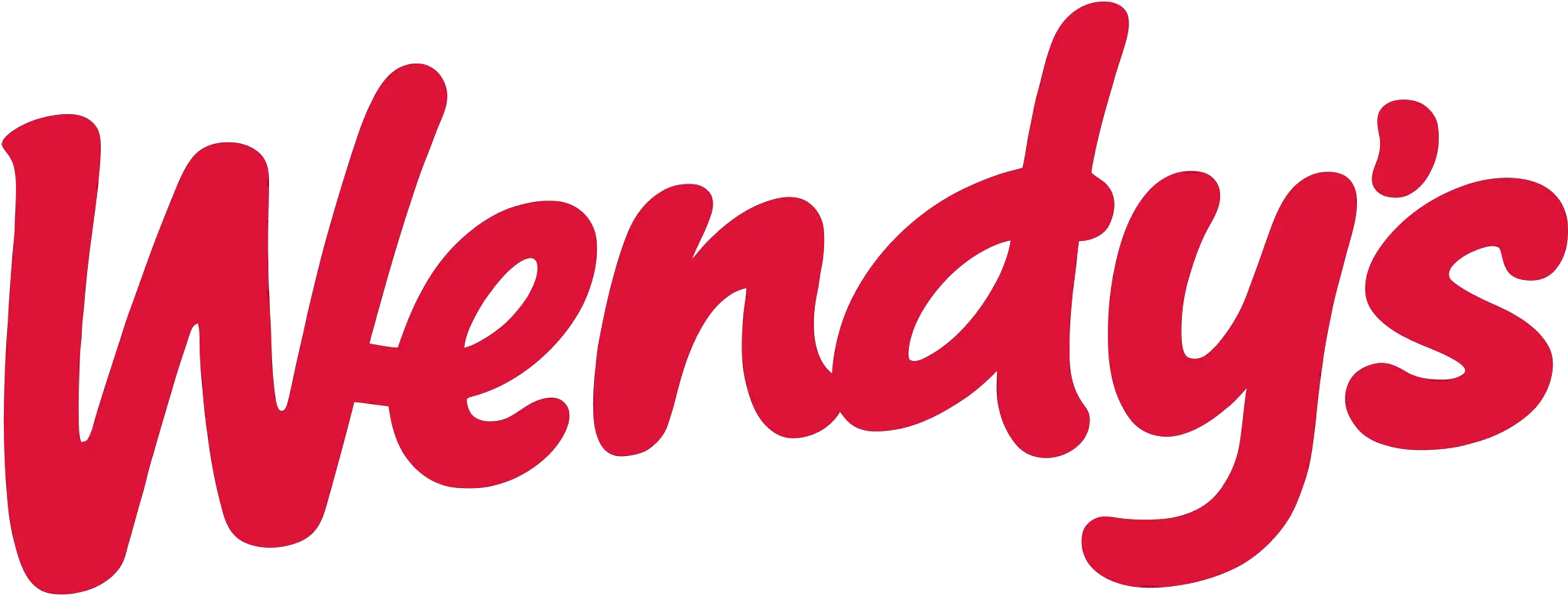
Wendys Logo Schriftart (alt & neu)
Wendys Logo verwendet welche Schriftart?
Bei der Gestaltung des Logos von Wendy wurde ein bestimmter Satz von Spezifikationen befolgt, aber es ist schwierig, eine bestimmte Schriftart zu bestimmen, die für die Erstellung des Logos verwendet wurde.
Trotzdem sind die Wendy's Script- und Wendyville- Schriftarten der Wendy's-Logotype-Schriftart auffallend ähnlich, die sich auf Wendy's Script überträgt.
Alternativen und ähnliche Schriftstile zu Wendy's Script und Wendyville
Das Folgende sind 5 Schriftarten, die im Design und in der Verwendung mit Wendy's Script und Wendyville identisch sind, wenn Sie nach einer Alternative oder einem ähnlichen Stil zu diesen beiden Schriftarten suchen:
- Amsterdamsk Schriftart
- Burtons Nightmare Schriftart
- Nightwish-Schriftart
- Siziliens Traumschrift
- Wendys Handschrift Schriftart
Wer hat die Wendys-Schriftart entworfen?
Der Designer der Schriftarten Wendy's Script und Wendyville ist derzeit noch unbekannt, aber es wird spekuliert, dass beide Ende der 1950er Jahre von einem amerikanischen Schriftdesigner namens Gert Wagner entworfen wurden.
Bekannt für viele von ihm entworfene Schriften, darunter ITC Souvenir, Handel Gothic und Times Roman, war Wagner ein herausragender Schriftdesigner.
Ein Überblick über Wendys
Es ist eines der bekanntesten Fast-Food-Restaurants in den Vereinigten Staaten, vor allem wegen seiner Sandwich-Kombinationen, Salate und Frosties. Wendy's Restaurantkette wurde 1969 gegründet.
Im gesamten Branding-Material von Wendy's wurden die Schriftarten Wendy's Script und Wendyville im Laufe der Jahre verwendet, aber ihr ikonisches Logo ist seit 1969 unverändert geblieben.
Es gibt viele charakteristische Details dieser Schrift, die als Teil der Marke Wendy's erkennbar geworden sind und oft als „die Typografie von Wendy's“ bezeichnet werden.
Eine Vielzahl anderer Elemente bilden die Corporate Identity von Wendy, wie die klassische rote, weiße und schwarze Farbpalette, die Verwendung ihres Maskottchens und die ikonische Beschilderung des Unternehmens sowie eine Vielzahl anderer Elemente.